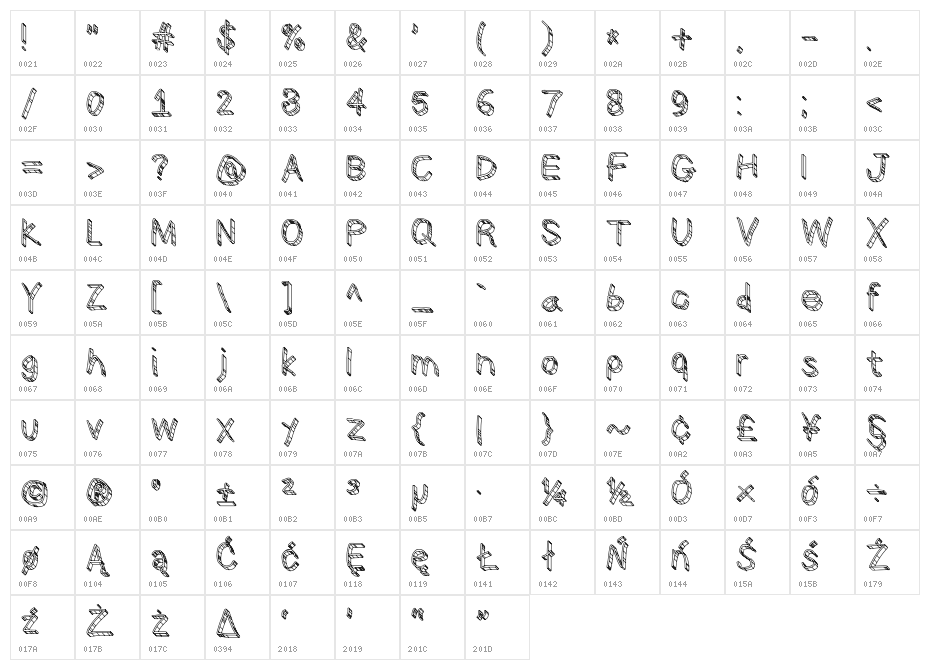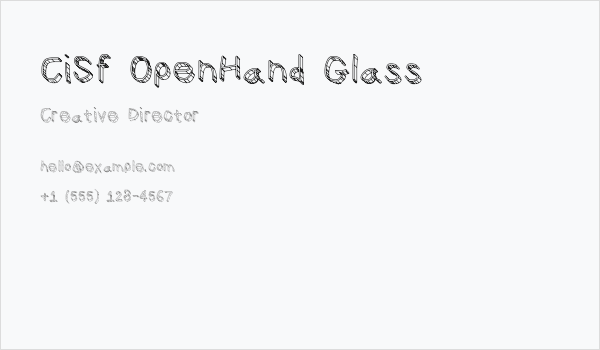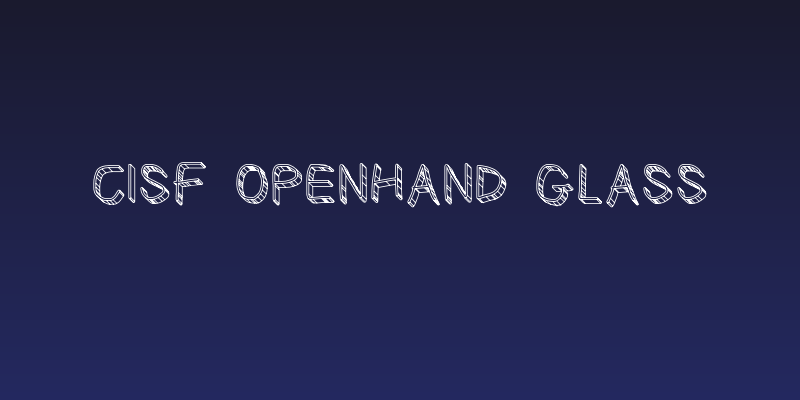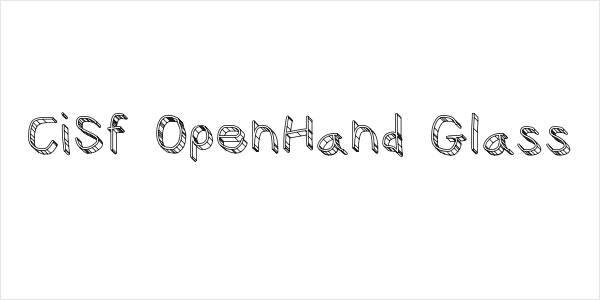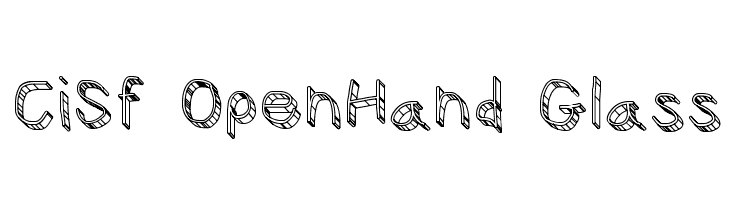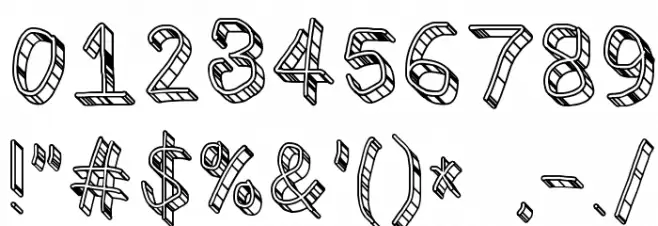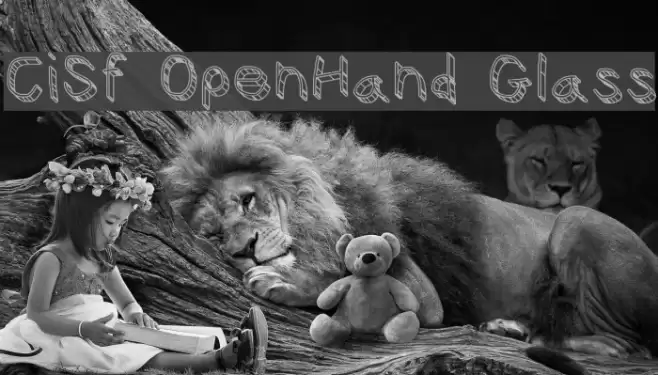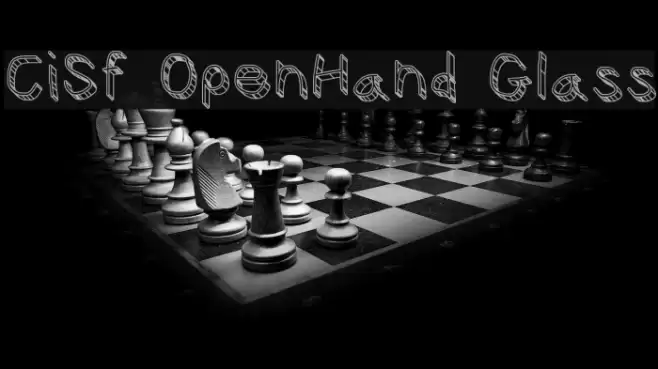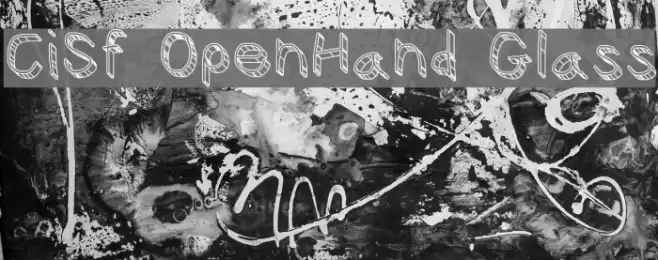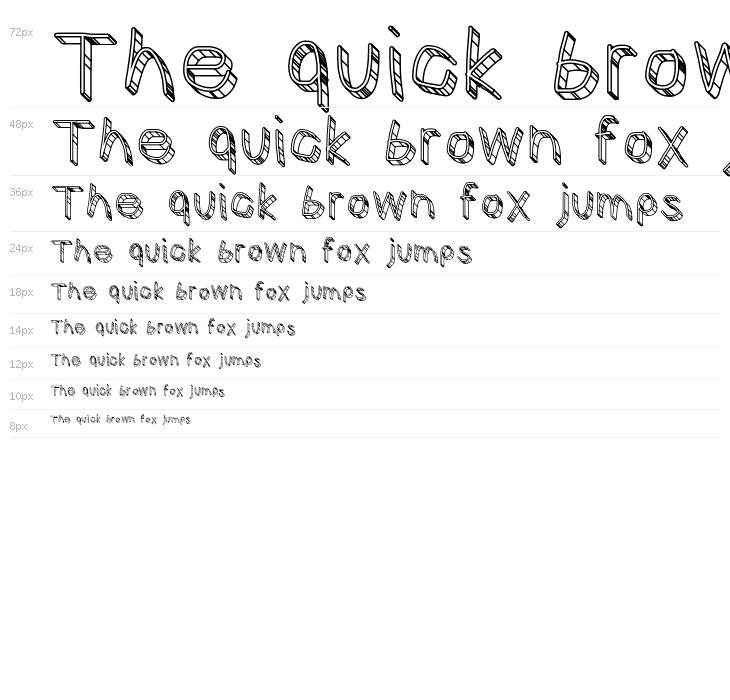
CiSf OpenHand Glass Font
| Gesamtstil | Playful, Whimsical, Informal |
| Anwendungsfall | Headlines, Posters, Creative Projects |
| Vorgeschlagene Projekte | Ideal for children's books, comic strips, playful branding, and creative posters. |